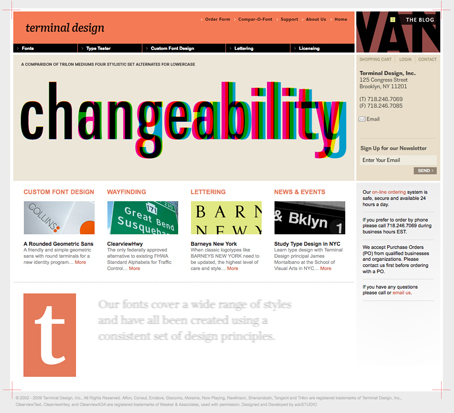
La fundición tipográfica digital norteamericana Terminal Design, fundada en 1990 por James Montalbano, renueva imagen y contenidos. Reconocida mundialmente por el lanzamiento de fuentes como la Clearview Type, (un ambicioso proyecto tipográfico que se promociona como un sistema de fuentes definitivo diseñadas para un uso global que se puede utilizar desde maquetación de textos hasta señalización de autopistas y que ha llevado casi 14 años de elaboración) o por el diseño de Consul, (una romana moderna con un marcado estilo didona, usada actualmente para la versión masculina de la revista Vogue), Terminal Design se apunta a la moda de las webs con apariencia blogger, consiguiendo un aspecto gráfico claro, más limpio, de fácil navegación y así de paso poder presentar nuevas secciones como el Type Tester (para probar las fuentes antes de adquirirlas) o el blog (ya inevitable en todas las webs de este tipo). También se ha aprovechado este cambio de imagen para lanzar al mercado todo un nuevo arsenal de fuentes de estilos muy variados y que amplían el ya de por sí abultado mercado tipográfico.
Algunos ejemplos pueden ser la Familia Trilon, una grotesca con nada más y nada menos que 80 estilos diferentes (y con una variedad de opciones Open Type casi ilimitadas) o la Rawlinson Roadway, una versión expandida de la tipografía que diseñaron para los servicios del Parque Nacional de los Estados Unidos. Tal como reseñan en su mail promocional: “¡Nuestro nuevo website se ha diseñado para hacer la visión y la compra de nuestras fuentes más fácil, más diversa y también con nuevos precios!” En el reino de los ciegos, el tuerto es el rey… y en el apartado de la venta de tipografías por internet, no actualizarse puede suponer la desaparición del mercado; Y en eso, lo americanos saben un rato…![]()